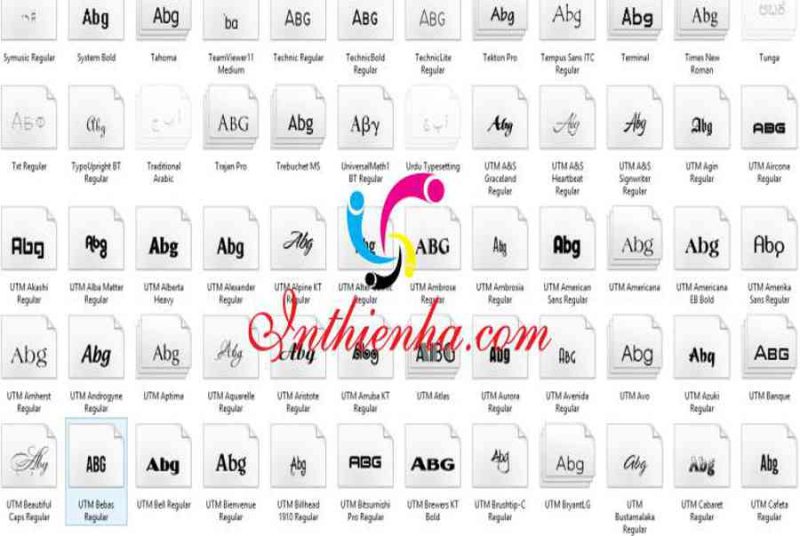
Font là một công cụ quen thuộc với những người làm công việc thiết kế trên máy tính. Hoặc các thiết bị điện tử có thể viết chữ. Có vô số những bộ font khác nhau mang những nét riêng biệt độc đáo. Thích hợp với từng mục đích khác nhau của người sử dụng. Trong đó bộ font UTM là một sự lựa chọn tuyệt vời cho những người yêu thích cái đẹp độc đáo. Theo hơi hướng nghệ thuật, khi ứng dụng các thiết kế đồ họa. Thiệp chúc mừng với dạng font viết tay, thư pháp đẹp.
Font chữ UTM là gì?
Font UTM gồm những font chữ viết tay, nét đậm, nét mảnh khác nhau. Thường được dùng khi phong cách thiết kế những loại sản phẩm trang trí, thiệp chúc mừng năm mới, aption ảnh, tiêu đề ảnh, bài thơ. Font UTM thích hợp với bộ gõ tiếng Việt Unikey và Vietkey. Sử dụng thuận tiện trên những ứng dụng Photoshop, ProShow Producer …, chat như Zalo, Skype, Viber, Halo …
Cho nên với bộ font này bạn hoàn toàn có thể tha hồ lựa chọn những phong thái chữ khác nhau. Phục vụ cho việc làm và mục tiêu phong cách thiết kế mẫu sản phẩm của mình .
Font Chữ UTM Việt Hóa
Có thể nói bộ font UTM là bộ font rất nổi tiếng trong hội đồng phong cách thiết kế. Bởi nó có nhiều font rất đẹp, trên cơ sở này. Nó đã được Việt hóa rất chuẩn tạo nên bộ font chữ phong phú. Phong phú về mẫu mã phòng cách được dân phong cách thiết kế vô cùng yêu quý. Và thường vận dụng cho những loại sản phẩm phong cách thiết kế của mình .
Trong đó, một số ít font điển hình nổi bật được việt hóa nhận được sự yêu dấu như UTM Traijan Pro. UTM God’s Word, UTM Khuccamta, UTM Essendine Caps. Đây là những font chữ thường vận dụng cho những phong cách thiết kế mang hơi hướng cổ xưa. Phong cách vintage hoặc những mẫu sản phẩm phong cách thiết kế về cuộc chiến tranh, caption can đảm và mạnh mẽ … .
Những lí do nên dùng font UTM Việt hóa để thiết kế?
Nếu hỏi những nhà phong cách thiết kế chuyên nghiệp nguyên do tại sao lại chọn dùng font UTM Việt hóa. Cho mẫu sản phẩm của mình thì bạn sẽ nhận được câu vấn đáp chung như sau :Font UTM Việt hóa này sẽ giúp bạn thỏa sức phát minh sáng tạo với dạng chữ thư pháp cực đẹp. Cung cấp không tính tiền nhiều font phong cách thiết kế thích mắt. Phù hợp với nhiều mục tiêu phong cách thiết kế khác nhau. Và đặc biệt quan trọng nó như được sinh ra cho tiếng Việt nên sử dụng thuận tiện. Và phong phú cho nhiều loại việc làm khác nhau .